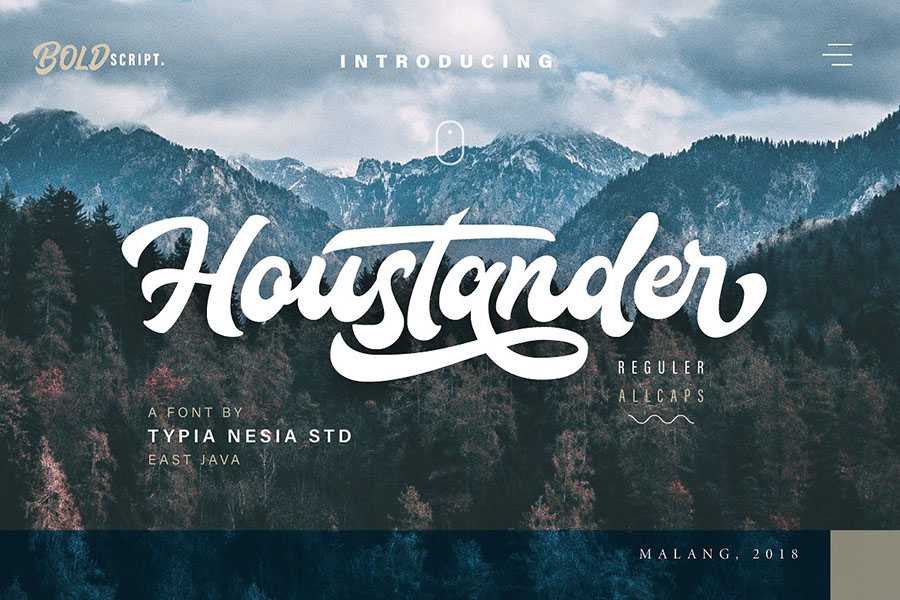
A fonte Houstander Script é uma escolha perfeita para quem busca harmonia na tipografia para designs variados. Desenvolvida por Hamilton, ela oferece um toque autêntico e fascinante que se adapta perfeitamente a vários projetos de design moderno. Ideal para aplicar em elementos como logos, branding, publicidade moderna, anúncios de logotipo ou headline, títulos de livros, cartazes, sites ou blogs, cartões promocionais, mugs personalizados, almofadas, camisetas com textura manuscrita e qualquer outra necessidade design específica. Com sua elegância e simplicidade, Houstander Script é uma fonte versátil que se destaca em qualquer projeto de design onde desejar combinar estilo e sofisticação.